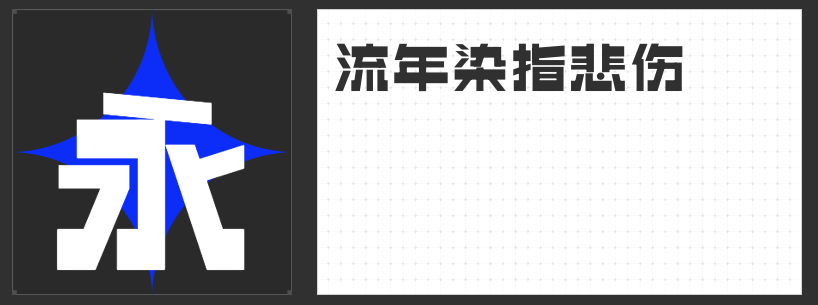
品牌视觉的锋芒之选:四款高辨识度商用字体推荐
在品牌设计的视觉战场中,字体是传递品牌气质的无声语言。一款兼具个性与功能性的字体,能瞬间强化品牌记忆点,在信息洪流中脱颖而出。以下四款专为品牌场景打造的商用字体,以独特的设计语言诠释了现代设计的力量美学。
一、励字钧线黑简
这款字体以全直线切割构建字形骨架,棱角分明的转折处暗藏力学美感。设计师通过精准控制笔画粗细比例,在保持黑体结构稳定性的同时,用斜度微调打破传统黑体的刻板印象。其极简的几何形态既符合数字化时代的审美趋势,又能通过负空间设计降低视觉疲劳,尤其适合科技、建筑类品牌的视觉系统构建。
二、励字勇敢黑简 特黑
当品牌需要传递坚定态度时,这款特黑字体堪称视觉利器。去衬线设计强化了笔画的雕塑感,粗壮的横竖笔画形成强烈的视觉张力,而收笔处的钝角处理则消解了锐利感,在保证远距离识别性的同时,赋予文字更温暖的触感。这种刚柔并济的设计语言,使其成为运动、汽车等强调力量感的品牌首选。
三、励字志向黑简 超粗
针对数字媒介的显示特性,这款超粗字体创造性地融合圆体与黑体特征。通过在笔画拐角处植入微弧曲线,既保留了黑体的稳重感,又用圆角缓冲了视觉压迫感。这种设计不仅让字体在高清屏显中呈现更饱满的形态,其适中的字腔比例更确保了小字号下的可读性,完美适配移动端品牌视觉体系。
四、高手兵克厚黑体
取法传统碑刻的宽扁结构,这款厚黑体以2:3的宽高比重塑汉字形态。设计师通过强化横细竖粗的对比关系,营造出如金石篆刻般的厚重质感。而笔画交接处的微妙弧度处理,则在刚劲中注入一丝东方气韵,使其既能驾驭传统行业的品牌升级,也可为文化创意类品牌注入历史厚重感。
在品牌同质化的今天,字体的选择早已超越信息传递的基础功能,成为品牌差异化竞争的战略工具。这四款字体通过各自独特的设计哲学,为品牌提供了从理性到感性、从传统到未来的多元表达可能。